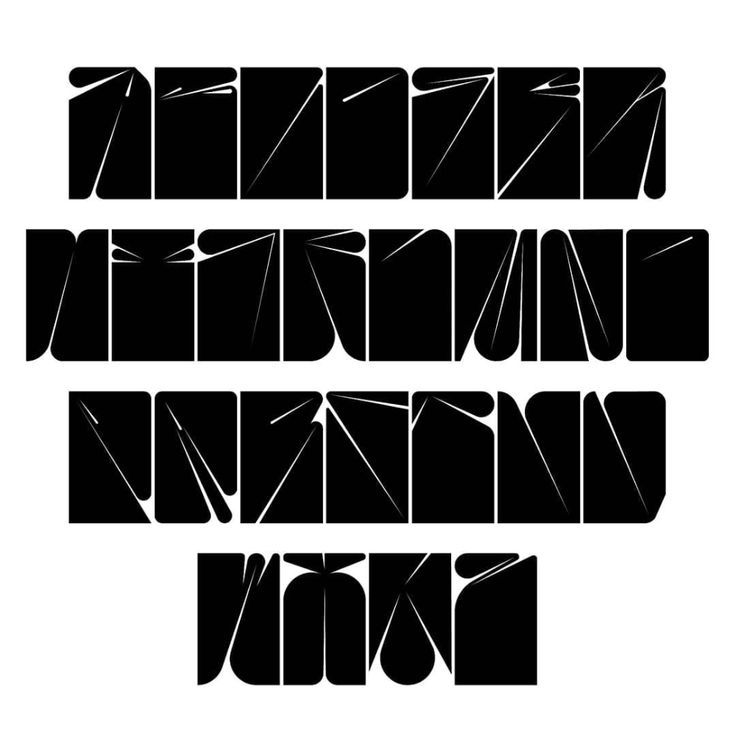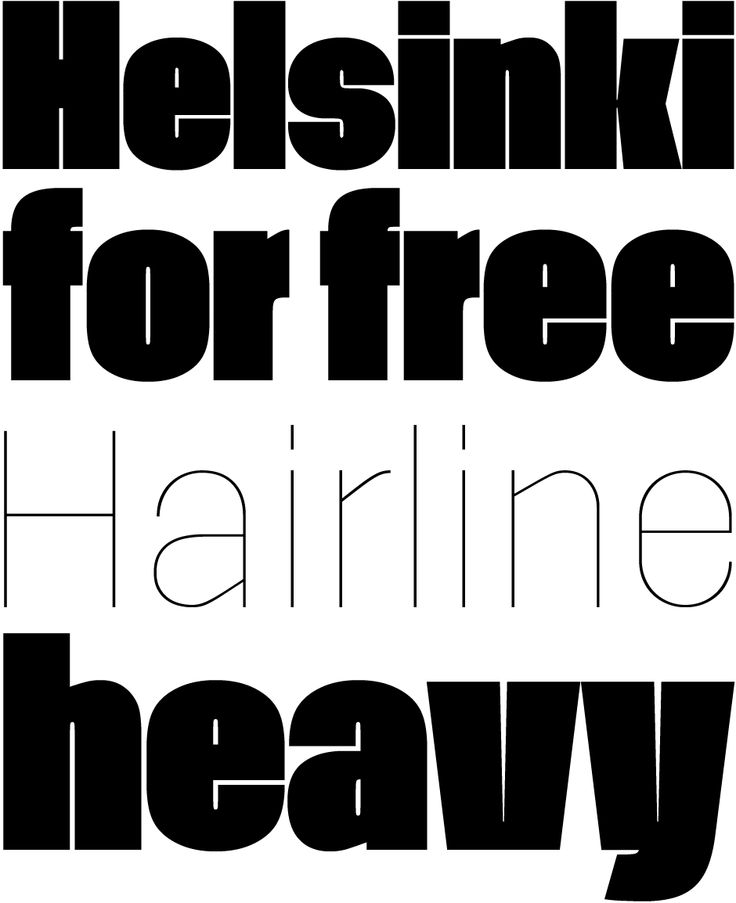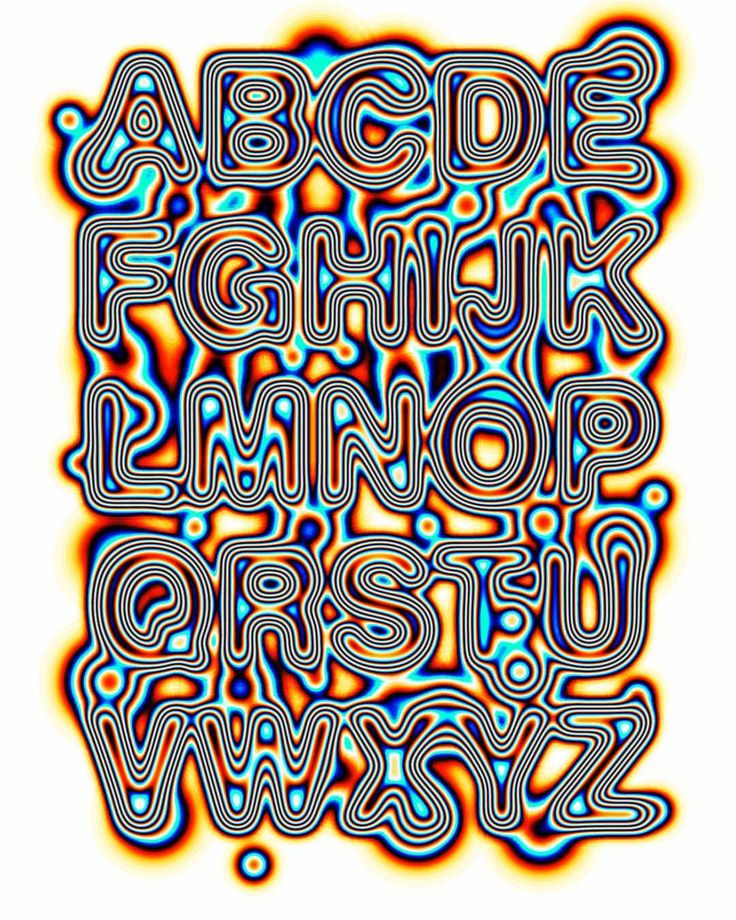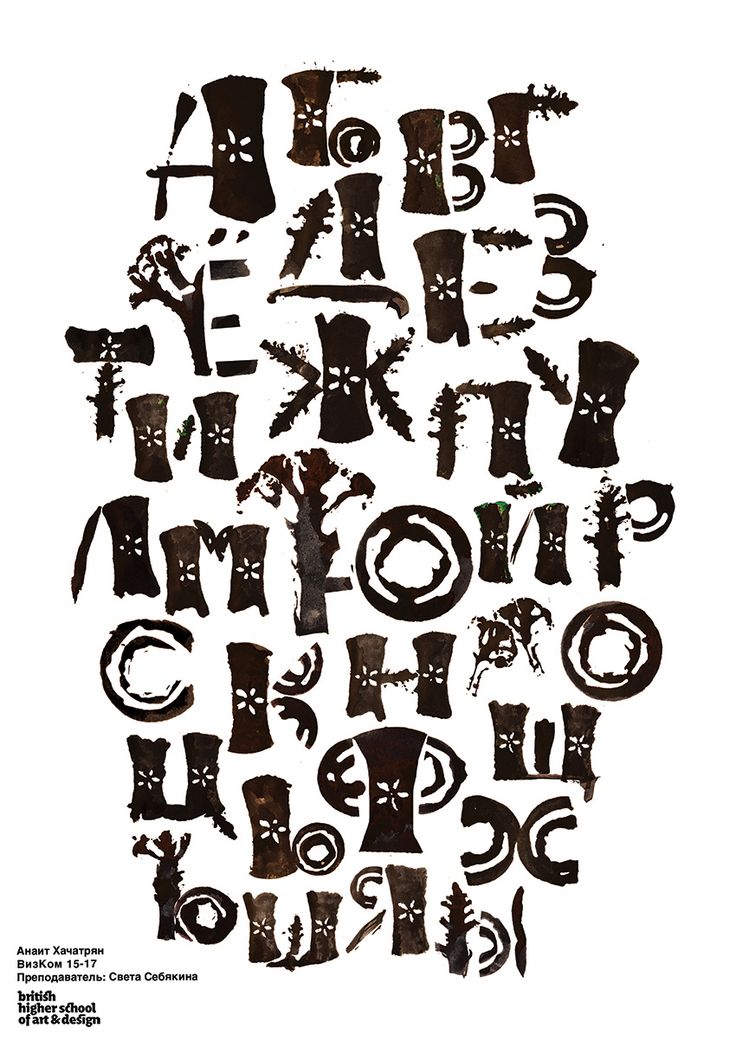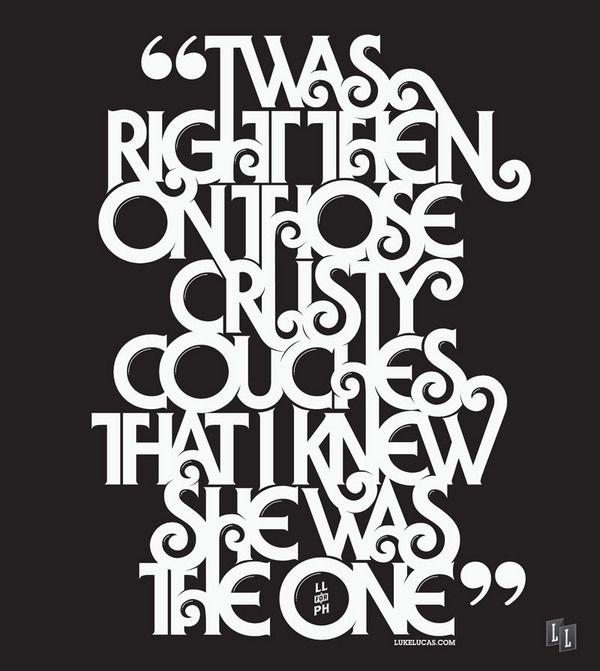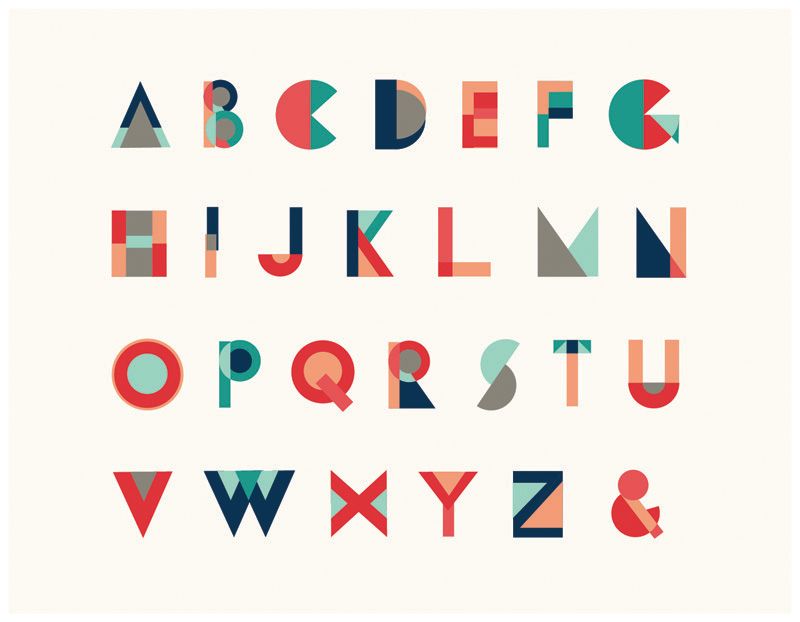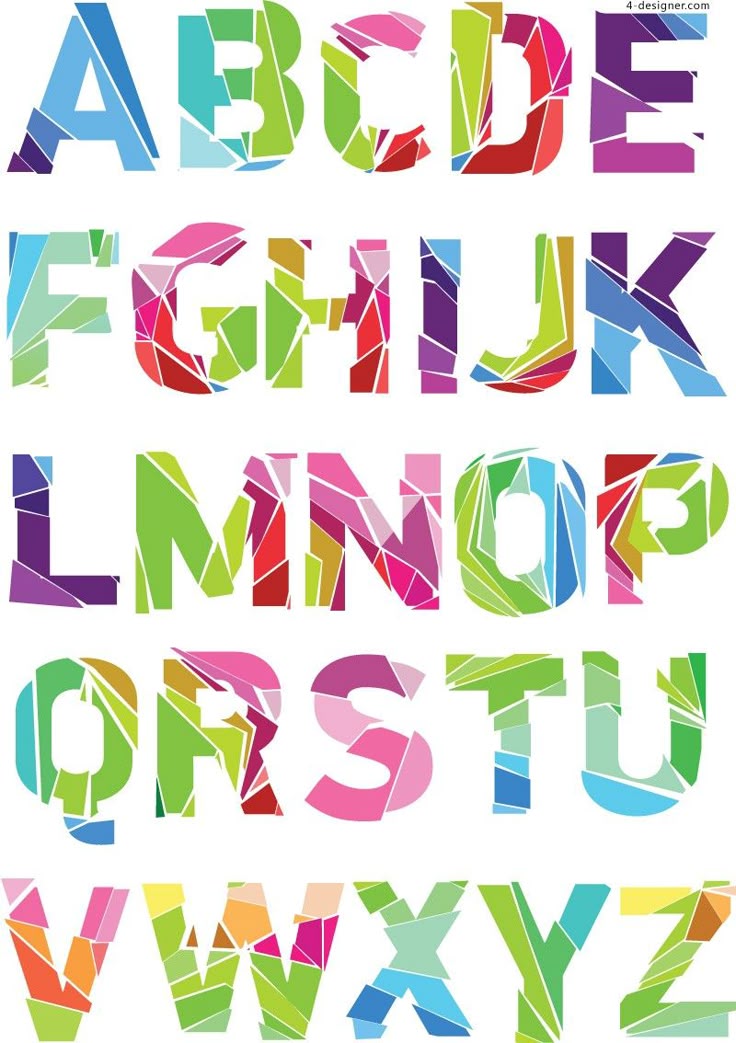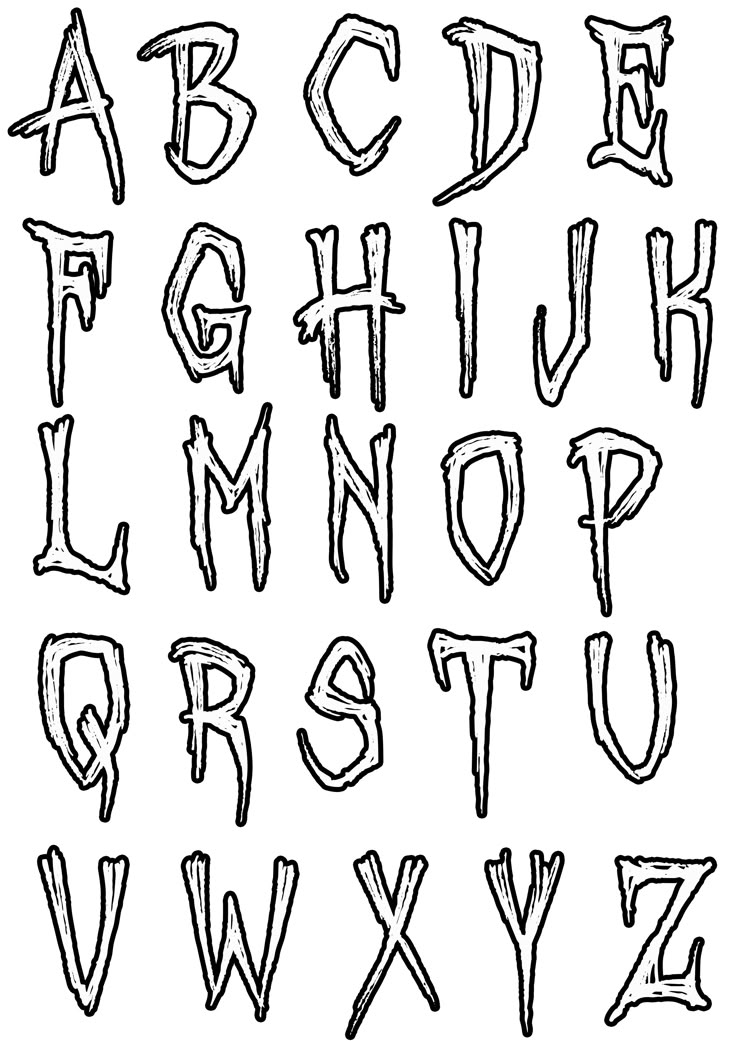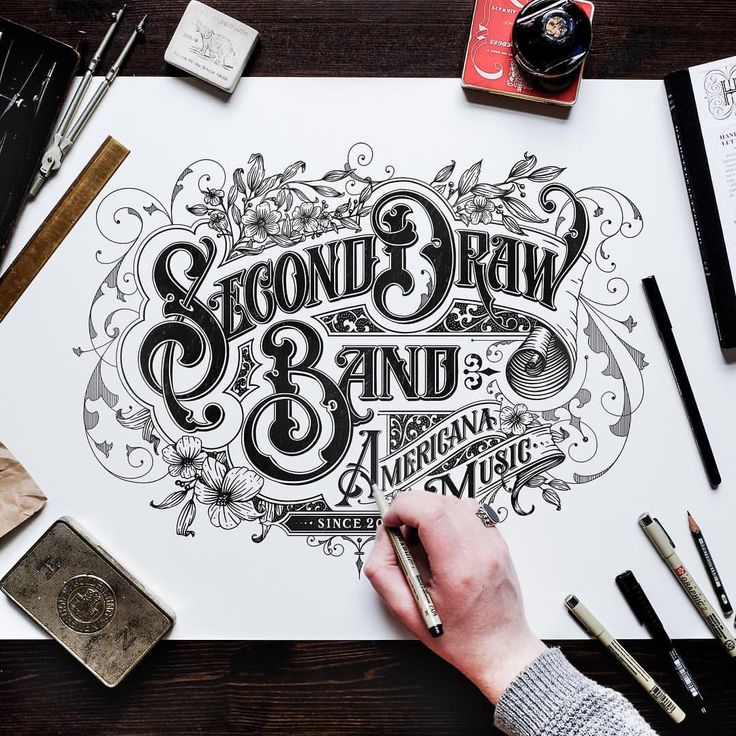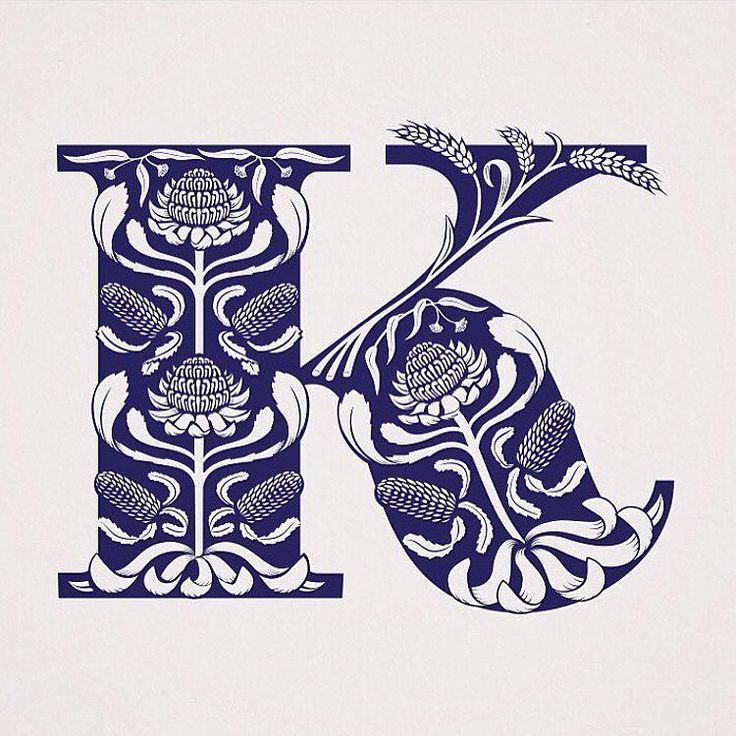
Дизайнерские шрифты: Дизайнерские шрифты
100 лучших бесплатных шрифтов для дизайнеров на 2020 год
Сегодня
типографика играет в вебе центральную роль, и передовые технологии — вариативные шрифты, CSS Shape, FlexBox, CSS Grid и Subgrid — в корне меняют то, как мы работаем с текстом в веб-дизайне.Ключевой элемент этого визуально привлекательного тренда — использование типографики с характером, она добавляет композиции ритм и контраст. Антиквы и акцидентные шрифты преобладают, но основной принцип создания отличных макетов заключается в сочетании нескольких шрифтов с кардинально разными характеристиками, весами и стилями, когда они идеально гармонируют и вместе создают сильное визуальное впечатление.
Приятно видеть как в последнее время всё чаще встречается кинетическая типографика с использованием долгожданных вариативных шрифтов. Каждый день в сети появляются новые результаты экспериментов с анимированными вариативными шрифтами и их свойствами, с применением эффектов вроде обтекания текста с помощью CSS Shape, и многих других, ставших популярными благодаря таким пробам.
Ещё одна хорошая новость: обновление Google Font API даёт возможность использовать 10 уникальных высококачественных и совершенно разных вариативных шрифтов — среди них брусковые, моноширинные, антиквы и гротески.
22. Шрифт Elanor от Dirtyline Studio
Elanor — новый свежий и современный шрифт с засечками в ретро-стиле, смешанный с экспериментальными штрихами! Так красиво на приглашениях, таких как поздравительные открытки, материалы для брендинга, визитки, цитаты, плакаты и многое другое!
23. Nighty — Бесплатный шрифт
Nighty — это шрифт для дисплеев, который говорит, что мы здесь, чтобы ностальгировать! Вдохновленный винтажным журналом, он возвращает атмосферу 70-х с заводным, ретро и уникальным шрифтом.
24. Шрифт Casta